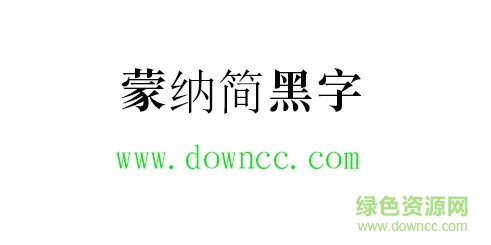
蒙納簡(jiǎn)黑體是一款完全免費(fèi)的電腦字體軟件,字體行云流水簡(jiǎn)單大方,可用于簡(jiǎn)單的設(shè)計(jì)創(chuàng)作之中,而且用該字體所設(shè)計(jì)的文字信息都非常突出有特色,讓你的畫面也變得更加美觀哦,需要的朋友可別錯(cuò)過(guò)了,歡迎來(lái)綠色資源網(wǎng)下載使用哦。
蒙納簡(jiǎn)黑體是款用于美工設(shè)計(jì)方面的字體,該字體字形端莊、剛勁雄渾,看上去十分美觀,整體效果非常統(tǒng)一,且字庫(kù)完整,可以廣泛應(yīng)用于名片設(shè)計(jì)、宣傳海報(bào)、ppt、影視制作以及內(nèi)容用字等領(lǐng)域,有需要的朋友可以免費(fèi)下載收藏。
1.筆畫端正均勻,筆形清秀、舒展,結(jié)構(gòu)寬博;
2.橫豎筆畫粗細(xì)差別不明顯,可作為雜志和書籍的正文首選字體,